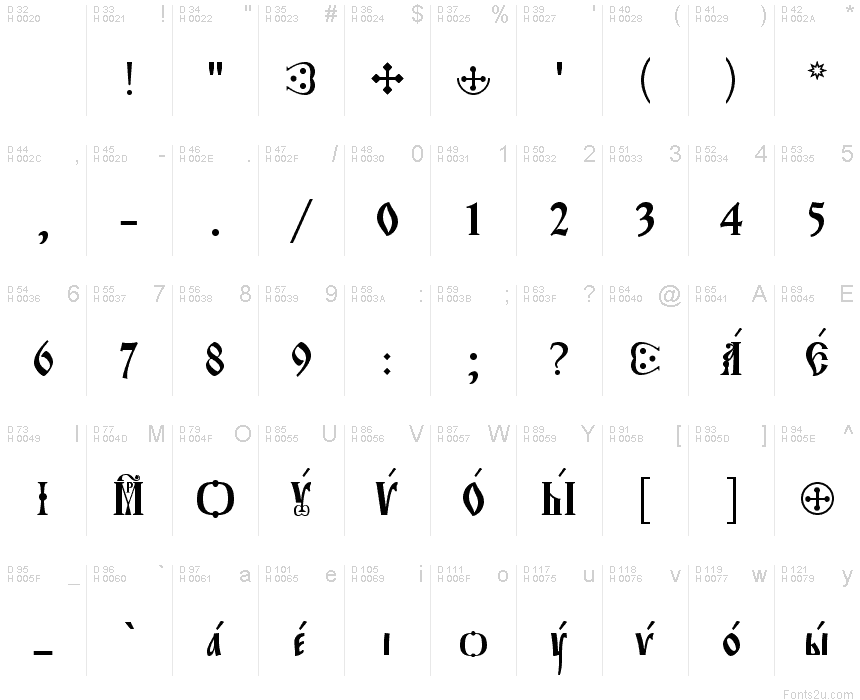
Orthodox, di SoftUnion Ltd e N. Andrushchenko, è un font display cirillico gratuito dal sapore liturgico ortodosso. Le lettere abbinano forme ovali ampie di stampo antico a piccoli punti, simili a perle, posizionati sopra e sotto, conferendo al font un ritmo cerimoniale ispirato alle icone, che appare più devozionale che puramente decorativo.
Questo rende il font gratuito una scelta naturale per bollettini parrocchiali, copertine di libri religiosi, locandine di festival, grafiche museali e titoli che richiedono un tono sacro slavo. Funziona bene anche per brevi intestazioni, iniziali e monogrammi, dove quegli accenti puntati ricorrenti e le curve importanti riescono a trasmettere l'intera atmosfera con poche lettere.
Evangelie, SoftUnion Ltd: 1994 -> Orthodox, N. Andrushchenko: 2003 Version 2.04
SoftUnion Ltd - A. Shishkin and N. Vsesvetskii; NAAsoft - N. Andrushchenko
Orthodox eRoos is a font which implements the Extended ROOS encoding that is containing Church Slavonic characters allocated according to the ROOS standard, Arabic numerals and special symbols (Typikon symbols, Mark's chapter symbols, etc). This font created on the basis of the font Evangelie by N. Andrushchenko